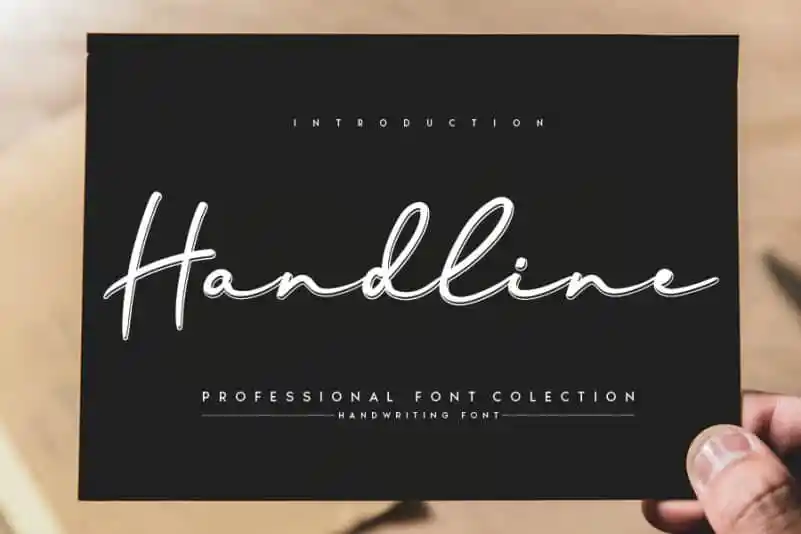
Handline Script Font – Download Grátis
A fonte ‘Handline Script Font’ é uma grife escrita a mão que oferece um toque sofisticado para qualquer projeto visual. Este estilo elegante e contemporâneo pode ser aplicado em múltiplas maneiras — não apenas para as postagens no Instagram, mas também em projetos DIY envolvendo calligrafia. Para designers buscando uma fonte de escrita a mão que complementa seus trabalhos de forma criativa e artística, esta é uma excelente escolha. Com ‘Handline Script Font’, qualquer ideia inovadora pode se transformar em um verdadeiro trabalho de arte. Seja para adicionar um toque autêntico ou criar um design único, essa fonte vai brilhar em qualquer projeto. Não importa o estilo da sua criação, ‘Handline Script Font’ é a escolha perfeita para expressar sua personalidade e tornar seu trabalho ainda mais incomparável.